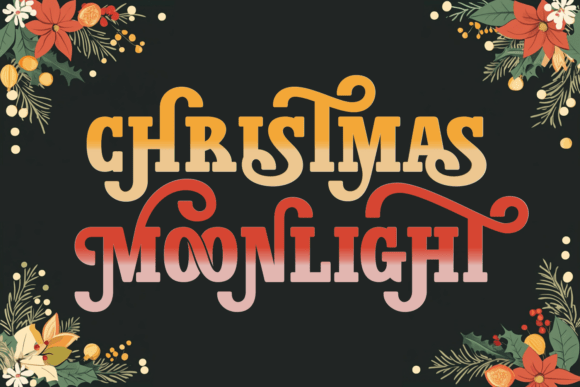
Christmas Moonlight
Att hitta rätt designelement kan vara utmanande, men Christmas Moonlight erbjuder en exceptionell samling som omedelbart lyfter ditt arbete.
Tillverkad med precision, ger Christmas Moonlight rena vektorer, smidig typografi och en kommersiell licens för sinnesfrid.
Oavsett om du skapar POD-produkter (Print on Demand), bröllopsinbjudningar eller grafik för sociala medier, är Christmas Moonlight ett perfekt val.